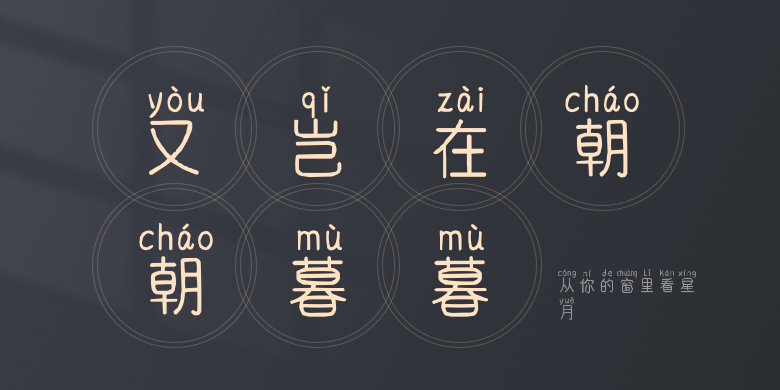
从你的窗里看星月
从你的窗里看星月,这款字体结构工整、笔画清晰,兼顾美观与易读性,适用于标题、正文、海报、包装、LOGO 等多种场景。字形优雅稳定,风格百搭耐看,适配日常排版与创意设计,让文字呈现更舒适、更具质感。从你的窗里看星月一笔一画,皆是细节,以均衡的比例、流畅的线条打造舒适视觉体验,字形端正大气,风格简约现代。无论是商业设计、品牌宣传还是日常排版,都能轻松驾驭,让文字更有格调与力量。从你的窗里看星月字体下载。